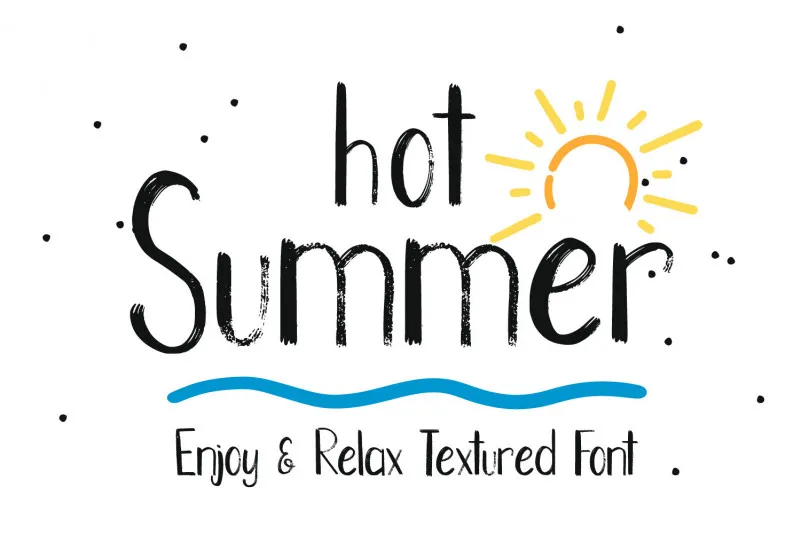
Hot Summer Display Font – Download Grátis
Esta fonte sans-serif é perfeitamente descritiva, com textura agradável que transmite uma sensação suave de calma e leveza. Ela também traz um duplo olhar inesperado, que pode soar sério para alguém e divertido para outra pessoa dependendo do contexto. Este design único torna-a perfeita para aplicar em qualquer projeto gráfico, como por exemplo, criar capas de roupas criativas, designs de tigelas, símbolos de marca, imagens de overlay, blog postagens, logotipos, convites e muito mais. Ela é uma fonte perfeita para quem está procurando um toque único e interessante em qualquer projeto visual que esteja trabalhando. Aproveite esta oportunidade de adicionar uma nota única a seu design com essa fonte inovadora!